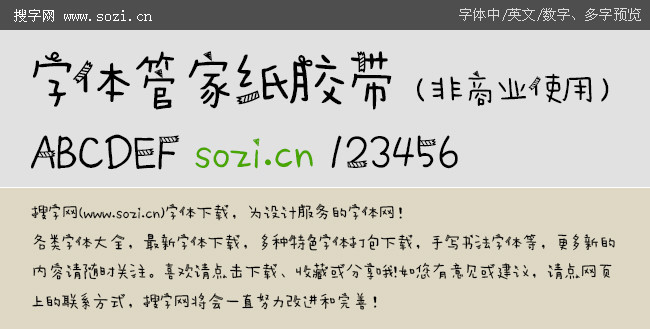
字體管家紙膠帶(非商用版)
搜字網(wǎng)給大家提供一款字體管家紙膠帶(非商用版)中文字體下載,該字體是一款卡通中文字體,字形有趣可愛,并裝飾有卡通圖案,充滿童真,適合兒童包裝設(shè)計、書裝設(shè)計、海報設(shè)計等應(yīng)用(此字體為個人非商用版,商用可以聯(lián)系QQ:1006760504)。